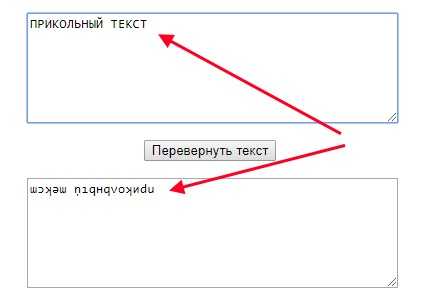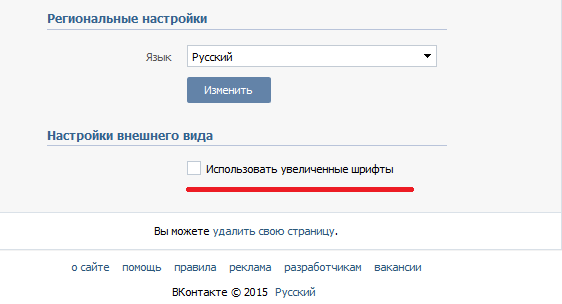
Как писать красивым шрифтом в вк: Красивые шрифты онлайн | Написать текст и скопировать
Как изменить шрифт ВКонтакте — TurboComputer.ru
Как изменить шрифт в вк на компьютере
Сегодня мы расскажем вам как можно изменить шрифт в социальной сети вконтакте и сделать его красивым и необычным.
Страница в социальной сети – это лицо её хозяина. Именно поэтому многие пользователи практически ежедневно работает над внешним видом своего виртуального образа, стараясь сделать его оригинальным и более заметным, увеличив тем самым количество друзей и подписчиков.
Одним из эффективных способов привлечения внимания к своей странице является изменения шрифта.
Как изменить шрифт в ВК на компьютере?
Подготовка к изменениям шрифта
До момента установки расширения для изменения шрифта необходимо сделать следующее:
1. Определиться какой веб-браузер будет использован
2. Выбрать шрифт
3. Выбрать размер шрифта
4. Решить какой цвет шрифта использовать
5. Выбрать плотность шрифта
Помочь в принятии решения по последним четырем пунктам сможет Word.
Так будут выглядеть надписи на странице после исполнения.Теперь можно приступать к решению вопроса, как поменять шрифт в ВК на компьютере.
Работаем с дополнением Stylish
• Откроем страницу в ВК и кликнем по иконке расширения Stylish
• В открывшемся окне нажимаем три вертикальные точки, в списке выбираем «Создать стиль»
• Откроется страница, в которой предстоит конструировать новый шрифт.
Сам себе дизайнер
• В поле «Код 1» необходимо внести следующие символы body
• Затем курсор нужно установить между фигурными скобками и два раза нажать клавишу «Enter»
• Последний параметр — цвет можно вписать еще одной строкой color: blue;
• Чтобы цвет стабильно отображался в ВК добавим в первую строку, после слова body запятую и символы div, span, a
Методом несложных манипуляций достигнут желаемый результат. Подчеркните свою индивидуальность! Будьте стильным ВКонтакте зная, как изменить шрифт!
Как изменить шрифт в ВК: инструкция для телефона и компьютера
Активные пользователи социальной сети интересуются, как изменить шрифт в ВК? Стандартный шрифт может надоесть, поэтому хочется чего-то нового. Функции сайта не предусматривают такой возможности. Но все же существуют способы изменения, о которых вы узнаете из нашей статьи.
Использование дополнения для браузеров
Перед тем, как изменить шрифт текста в ВК на компьютере, необходимо провести дополнительные процедуры для выбора стиля. С этим вам поможет текстовой редактор от Microsoft – Word.
Откройте новый документ и напишите любой текст. Затем с помощью стандартных инструментов выберите стиль шрифта, его цвет и размер. Таким образjv, вам будет легче понять, какое оформление вам нужно. После того, как подобранный стиль вас удовлетворит, запомните все его параметры: название и размер, чтобы в дальнейшем ввести эти значения редакторе.
После того, как нужное расширение найдено, нажмите на кнопку для запуска процесса инсталляции его в веб-обозреватель. Значок Stylish появится на панели расширений, а вы будете перенаправлены на стартовую страницу плагина. Здесь вы можете найти уже готовые стили, а также создать свою собственную версию оформления.
Для работы с ним необходимо авторизоваться, чтобы созданная тема была доступна и другим пользователям. После этого сделайте следующее:
• Перейдите на сайт Вконтакте и нажмите по иконке дополнения левой кнопкой мыши.
• В открывшемся окне вверху найдите иконку в виде трех вертикальных точек и щелкните по ней.
• В меню выберите пункт «Создать стиль».
Откроется редактор, где вам предстоит быть дизайнером своего стиля. Работать с ним не так сложно, как можно показаться на первый взгляд. Чтобы сделать другой шрифт в ВК, достаточно следовать инструкции: